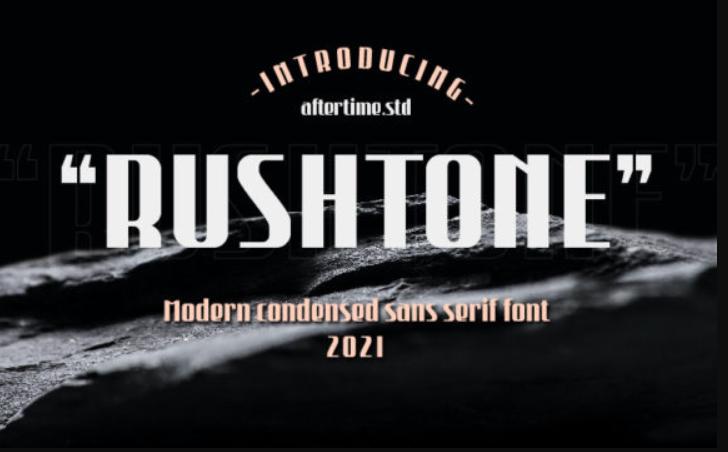
[Creativefabrica] Rushtone Font (AftertimeStudio)
Rushtone - это крутой, современный дисплей с толстыми буквами. Добавьте этот забавный шрифт в свои дизайны и обратите внимание, как он оживляет их!